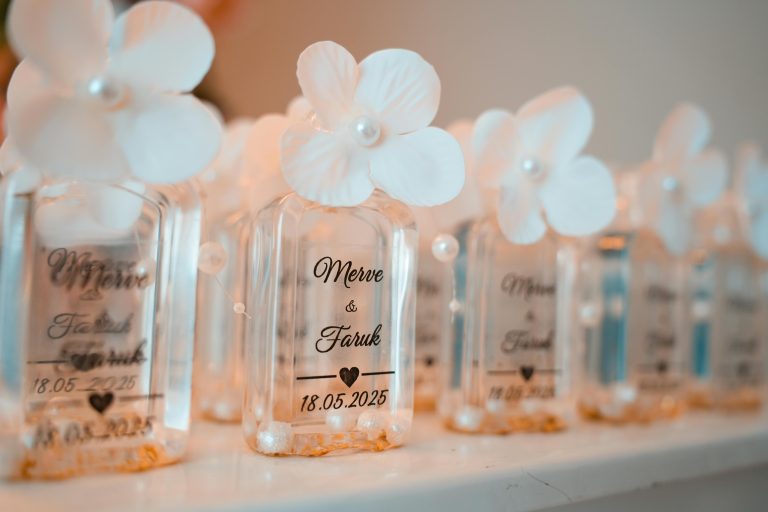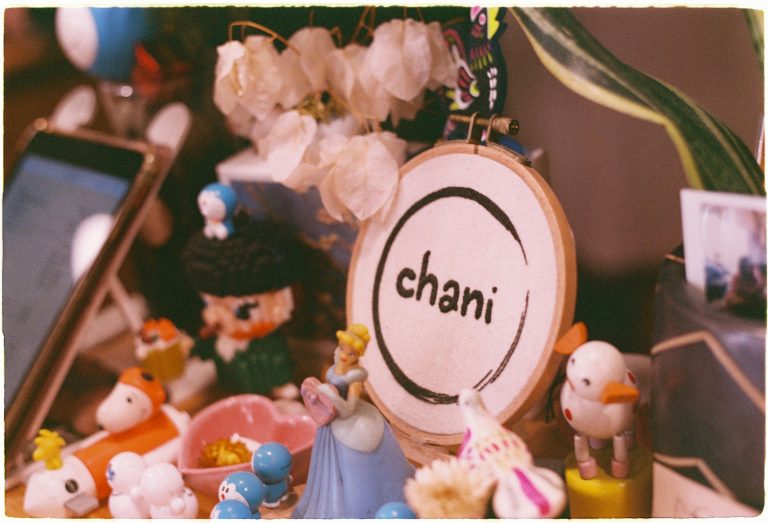
如何選擇好看的英文字體?避免這5個常見錯誤提升設計質感 [How to Choose Beautiful English Fonts? Avoid These 5 Common Mistakes to Enhance Design Quality]
隨著數位內容的廣泛普及, 字體的選擇已成為網頁設計中的重要一環 。好的英文字體不僅能提升網站的視覺美感,還能大幅改善使用者的閱讀體驗。然而,許多設計者在選擇字體時常犯一些錯誤,無形中影響了最終的設計質感。本文將探討如何選擇合適的英文字體,並列出五個需要避免的常見錯誤。
1. 字體的基本分類
首先,我們需要了解字體的基本類型,這主要包括 衬线体(Serif) 和 无衬线体(Sans-Serif) 。在選擇字體時,可以根據網站內容和目標受眾來決定使用何種字體。例如,若網站為學術類型,則使用衬线体會增加文章的正式感,反之則可以使用无衬线体來提高可讀性和現代感。
| 字體類型 | 特點 | 適合用途 |
|---|---|---|
| 衬线体 | 擁有字母筆劃邊緣的小裝飾,通常給人一種傳統和正式的感覺 | 書籍、報紙、學術文章 |
| 无衬线体 | 無邊緣裝飾,外觀更簡潔現代 | 網頁標題、廣告、科技產品 |
2. 避免的第一個錯誤:使用過多字體
許多設計師在網站上使用了 多種字體 ,導致整體風格缺乏一致性。過多的字體會讓讀者感到困惑,也會削弱網站的專業性。理想的情況下,一個網站中應該使用最多 兩到三種字體 。通常,選擇一種主字體作為正文,另一種作為標題已經足夠。
3. 避免的第二個錯誤:忽視字體的可讀性
選擇字體時, 可讀性是至關重要的 。一些造型獨特但可讀性差的字體可能會影響使用者的閱讀體驗。特別是對於長篇文本,使用可讀性高的字體能幫助讀者更輕鬆地吸收內容。可以選擇如 Merriweather 和 Roboto 等字體,這些字體在網頁閱讀上表現優異。
4. 避免的第三個錯誤:未考量設備和平台的兼容性
隨著不同設備的流行,設計網站時必須考慮字體在各種裝置上的顯示情況。某些字體在移動設備上可能並不易讀,因此應進行跨設備測試,以確保字體在不同平台下的一致性。
| 測試項目 | 桌面顯示 | 手機顯示 |
|---|---|---|
| 字體大小 | 大而明顯 | 適中清晰 |
| 行間距 | 合適,不擁擠 | 自然流暢 |
| 每行字數 | 不超過65個字符 | 更短,便於快速掃描 |
5. 避免的第四個錯誤:選擇過時或不流行的字體
在選擇字體時,使用過時的字體可能會讓你的設計顯得老舊或不專業。保持對趨勢的敏感,選擇當下流行的字體組合,可以讓你的網站更具吸引力。例如, Lora 與 Merriweather 的組合,就是當前設計界的熱門選擇。
字體的選擇在網站設計中至關重要,正確的字體不僅可以提升網站的視覺效果,還能增強使用者的閱讀體驗。避免上述提到的常見錯誤,並選擇合適的字體類型,可以讓你的設計更加出色。因此,在下一次設計網站時,請務必考量字體的選擇,讓你的作品更加引人注目。